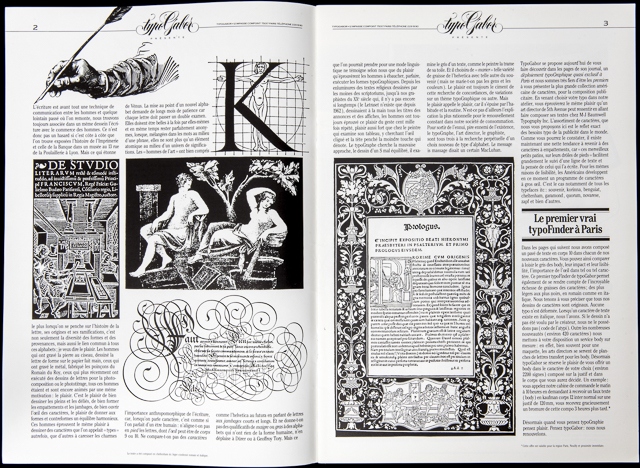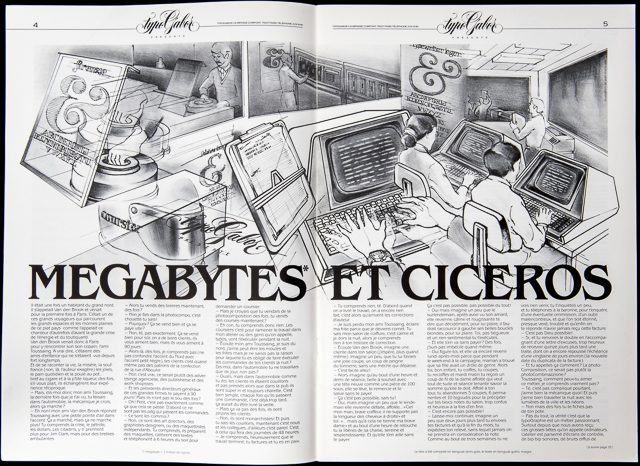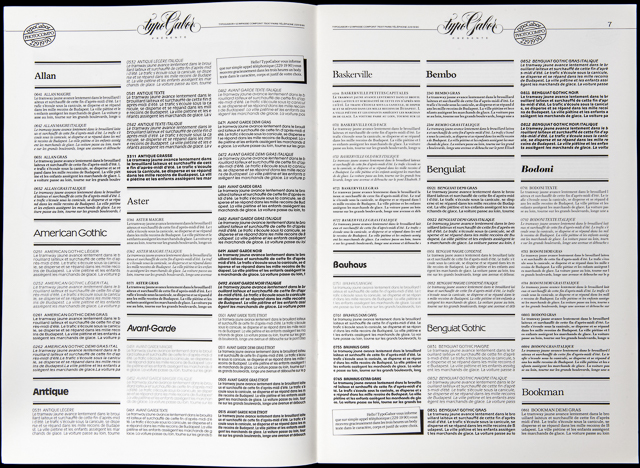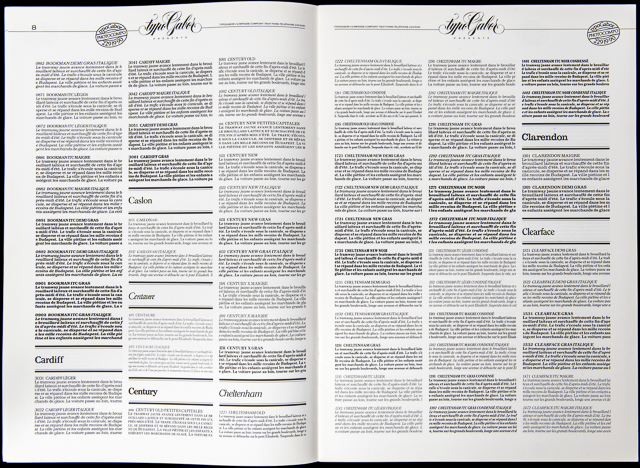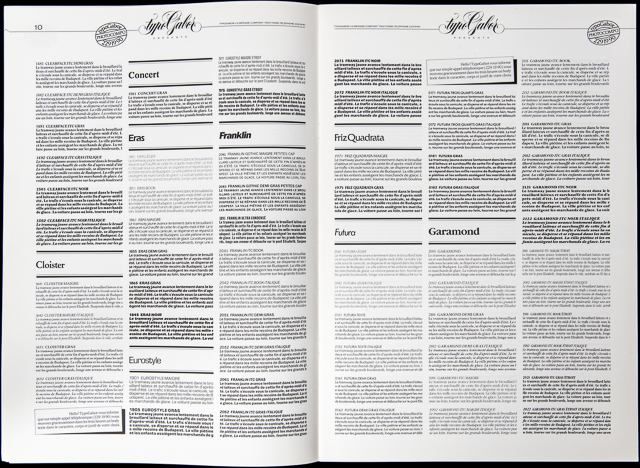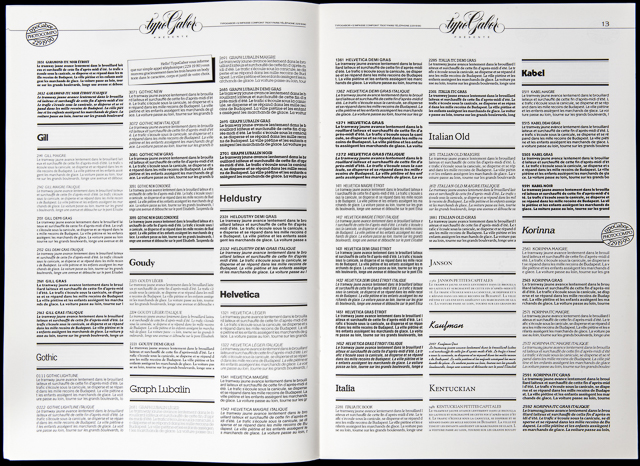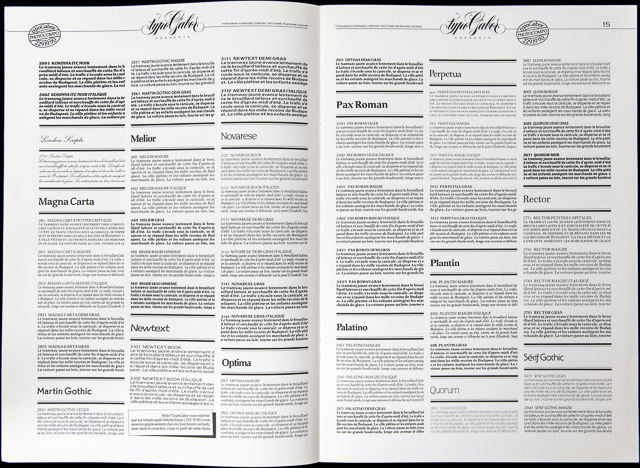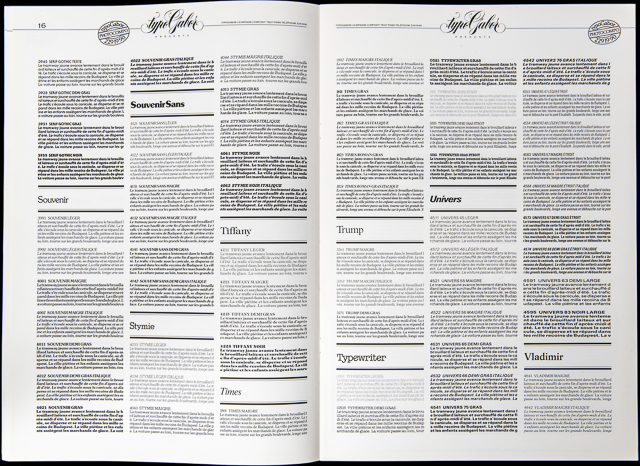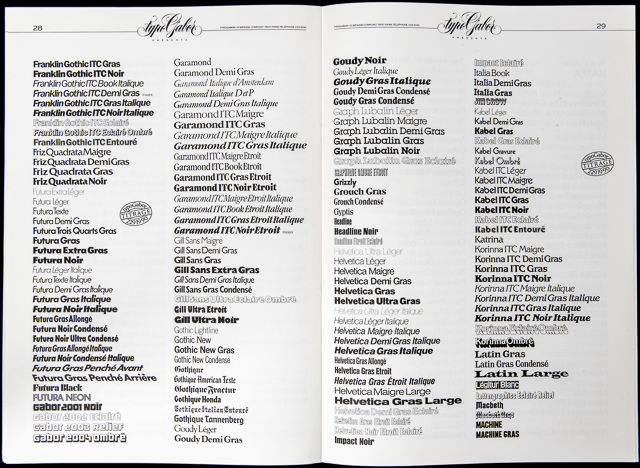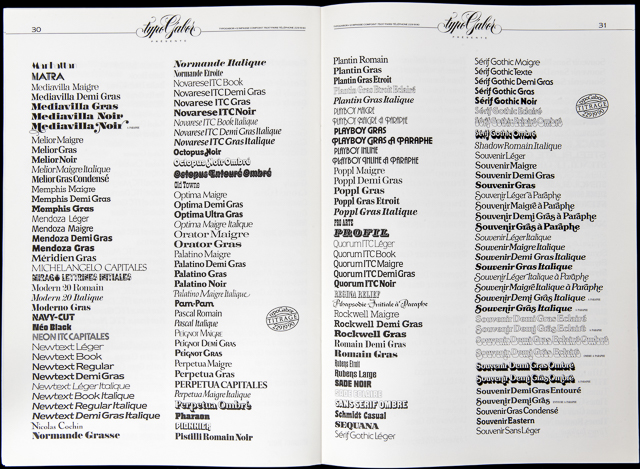
l’Histoire des Magazines typoGabor | N°2 | Allan, Lubalin, Benguiat
« TypoGabor présente »
N°2 | Allan, Lubalin, Benguiat
Même si certaines manifestations graphiques sont en germe dès 1968, typoGabor est fondée en 1973 par Paul et Peter Gabor. L’activité de la société est double : atelier de création graphique autour des clients historiques de Paul Gabor et société de services typographiques sous l’égide de Peter Gabor.
Les premières années de typoGabor sont rythmées par le fonctionnement coûteux et limité des Diatronic de Berthold. Tant et si bien qu’à la fin des années 1970, la continuité d’exploitation semble compromise. C’est à la faveur d’une annonce dans la revue CARACTÈRE que Peter Gabor découvre l’Alphatype. Il y voit l’amorce d’une révolution du digital. Ce sera son ami (depuis) Raymond Aubry, chef d’Atelier de Graphiservice à Bruxelles qui achèvera de le convaincre. Un système de composition américain venant de Chicago, qui pour la première fois, propose non plus d’acheter mais de louer (prix dérisoire) des polices de caractères, ce qui porte l’offre et la diversité typographiques à un niveau inédit : 1 000 polices contre 80 sur Diatronic auxquels s’ajoutent 16 polices supplémentaires tous les mois.
« typoGabor présente » naît en 1980 de deux constats. Il ne s’agit plus de faire de la Pub pour une entreprise, mais d’informer et d’éduquer un marché. La Publicité. Un marché où s’affrontaient une trentaine de concurrents proposant tous à peu près les mêmes services (24/24, coursiers, catalogues de calibrage gratuits et qualité de composition supérieure à celle de l’édition ou de la Presse). typoGabor connaît alors le succès. Les Directeurs Artistiques affluent et les commandes doublent de volume en l’espace de 2 ans.
Mais la formule marketing du magazine ne plaisait plus à Peter Gabor. Il y préféra une formule nouvelle autorisant toutes les expérimentations typographiques. Le magazine littéraire de typoGabor était né. Plusieurs directeurs artistiques vont se succéder dans les cuisines typographiques de la maison Gabor. Bill Butt, Jérôme Binda, Philippe Duriez et pour finir Paul Gabor qui revient en 89 par une magistrale œuvre consacré aux Droits de l’Homme. L’Âge d’Homme.
L’expérience de la photocomposition fut de courte durée. Le Postscript arrive sous la forme commercialisée d’Adobe Type Manager et tous les prestataires de composition perdent 50 clients par jour à partir de 1990. Peter Gabor tenta encore d’adapter son entreprise en devenant le premier compositeur qui a basculé la totalité de son fonds sur Macintosh. Mais les dettes s’accumulant et victime d’un administrateur judiciaire peu scrupuleux, il finit par baisser les bras, non sans avoir personnellement créé 4 polices de caractères pour le Journal Libération en 1994.
Une aventure de vie passée à promouvoir la diversité et la qualité de composition, parce que comme l’aimait à rappeler son père Paul, d’après une phrase de Jean Cocteau : «Le style n’est pas une danse mais une démarche».
• Où l’on voit que les textes sont assez dithyrambiques: mais le fait était là, typoGabor offrait pour la première fois sur le marché parisien un choix de caractères de composition inédit jusques là. Cette culture du choix nous venait sans doute de la première phase de développement de l’entreprise. Nous avions commencé comme un studio de Titrage. Or sur ce créneau de marché le choix typographique était l’un des facteurs de réussite. La qualité de composition en était son parfait complément.
• Quand j’ai découvert le système Alphatype à Bruxelles (après avoir vu l’info dans la revue CARACTÈRE), j’ai tout de suite saisi la novation qu’il nous apportait. Cette fonderie, ce fabricant de système de composition situé à Chicago, proposait non plus d’acheter les polices, mais de nous louer leur typothèque moyennant des redevances annuelles et une mise à jour quasi mensuelle. C’était bien moins onéreux que l’achat des polices Diatronic de chez Berthold. Ce fut une révolution dans les Agences de Publicité. Une avalanche de choix typographique de composition de texte. Du jamais vu auparavant à Paris. Ceci explique donc le style de communication assez «boy scout» je dois reconnaître. Mais nous vivions cela avec une passion démesurée.
• où l’on voit illustré les technologies que nous avions fait venir de Chicago. Front-end, Back-end. Les écrans de saisie, les photocomposeuses digitales qui composaient avec une définition de 5200 dpi (dot per inch), une prouesse technique. À gauche dans l’image l’on voit les unités de mémoires Control Data qui contenaient 300Mo de volume de texte. Et les unités de composition juste à côté. Tout le système était doublé en Sauvegarde miroir (style RAID) afin de ne jamais interrompre la production en raison d’une panne quelconque.
• Ici l’on montre l’activité du Studio Gabor que Paul Gabor dirigeait pendant que je développais l’atelier de composition. Bien sûr que j’étais souvent frustré. Si j’avais eu le choix, je crois que j’aurais préféré travailler à développer le studio de graphisme. Mais les responsabilités étaient telles qu’il m’était impossible de me couper en deux. Paul m’appelait très souvent pour me demander mon avis sur les créations, et je dois avouer que notre collaboration était marqué du sceau d’une complicité sans faille jusqu’à 1986. Rien ne sortait du Studio que nous n’ayons Paul et moi discuté, corrigé ensemble. Ma frustration était plus du coté de la réalisation. Il fallait déléguer, là où j’aurais sans doute préféré réaliser moi-même.
• Nous étions les premiers à recevoir tous les caractères ITC qui sortaient à New York. Parce que Alphatype en optant pour la technologie digitale s’était détachée des contraintes de fabrication très lourdes des polices de 2ème génération. Les dessins d’ITC fournis à Alphatype étaient directement numérisés, complétés avec un programme d’approches et de kernings, et immédiatement envoyés à tous les clients de la firme de Chicago dans le monde entier. Berthold, ou Compugraphic avaient besoin de plusieurs mois de travail assidu pour diffuser les mêmes polices fabriquées de façon photographique et traditionnelle.